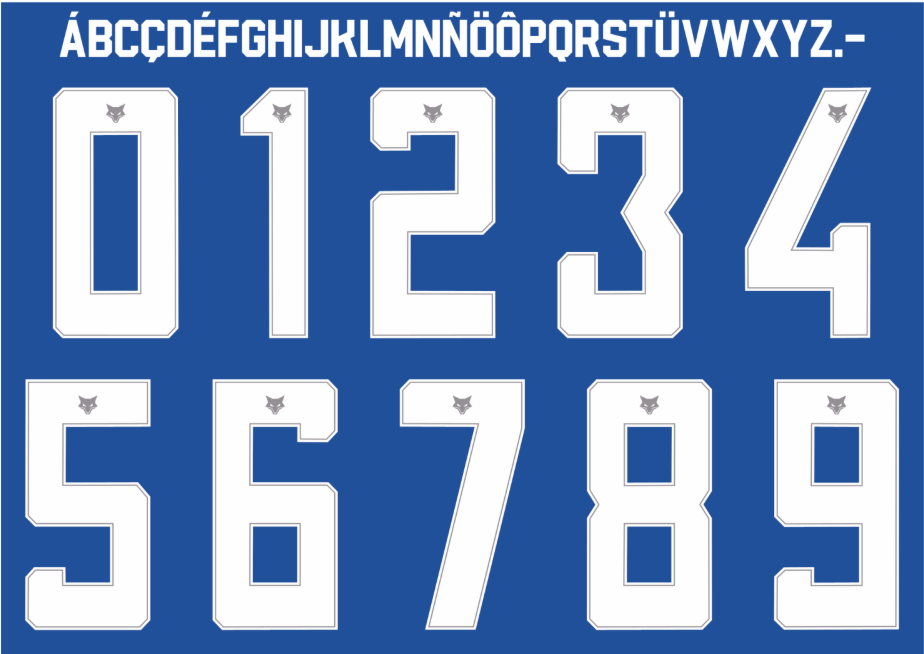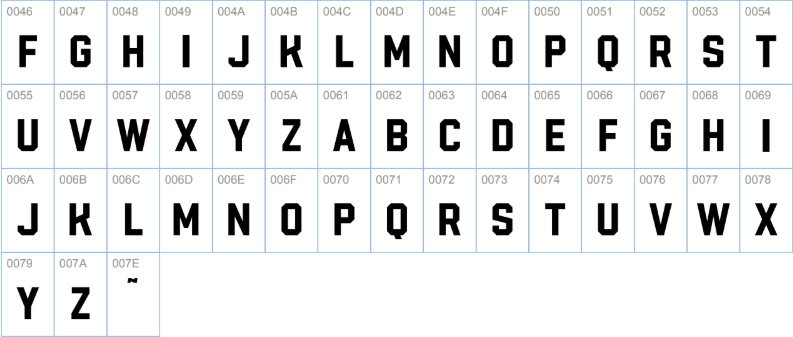
A temporada 2026 começou e a Nação Azul já está pronta para apoiar o Cabuloso em todas as competições. Seguindo a forte parceria com a Adidas, o Cruzeiro estreia seus novos uniformes trazendo uma identidade visual que honra a tradição estrelada, mas com a tecnologia de ponta da marca alemã.
Neste post, disponibilizamos o arquivo da tipografia oficial usada nas camisas titulares (Azul) e reservas (Branca) para que você possa personalizar seus projetos com o mesmo padrão visto no Mineirão.
Estilo Visual da Tipografia
A Adidas entregou para o Cruzeiro em 2026 uma fonte que mistura robustez com linhas dinâmicas. O design foge do padrão genérico, apresentando números com cortes angulares que remetem à velocidade e ao movimento do futebol moderno.
A legibilidade é um ponto forte: seja no clássico fundo azul ou na camisa branca, os caracteres possuem um peso visual equilibrado (bold), garantindo que o nome e o número do atleta sejam facilmente identificados tanto na arquibancada quanto nas transmissões em 4K. É a união perfeita entre a estética “Three Stripes” e a identidade do Maior de Minas.